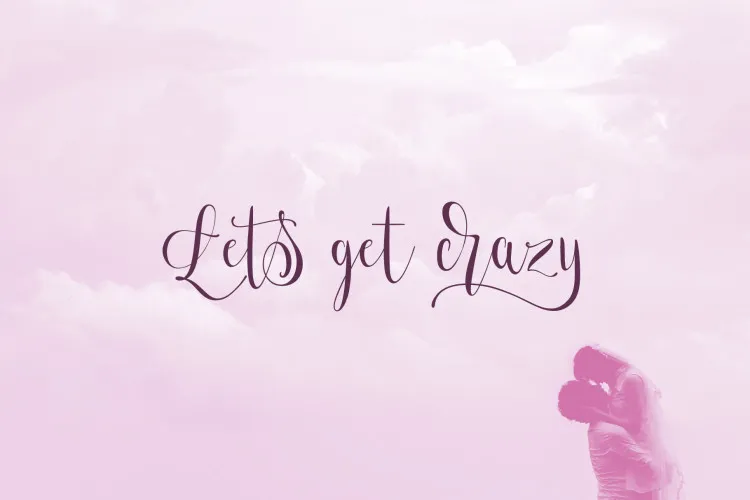
Lets Get Crazy Font Duo – Download Grátis
A fonte ‘Lets Get Crazy Font Duo’ é uma paleta única que combina a elegância das letras cursivas com o minimalismo do tipo serifado, criando designs luxuosos e logos impressionantes. Desenvolvida por vectalex, essa font surge da inspiração em letra moderna e caligrafia, apresentando características marcantes como swashes pronunciados, desníveis ascendentes e descendentes no ‘r’ (que você pode usar alternativas mais comuns), além de outras inovações que desafiam os limites convencionais. Esta combinação faz do Let’s Get Crazy Script um excelente escolha para títulos ou frases curtas, quando combinada com letras maiúsculas serifadas ‘Lets Get Crazy Sans’. A fonte é perfeitamente adaptável ao design moderno das letras, oferecendo uma harmonia única e vibrante. Se você está procurando por uma font que vai além da banalidade para criar designs de alta qualidade, essa pode ser sua opção ideal.